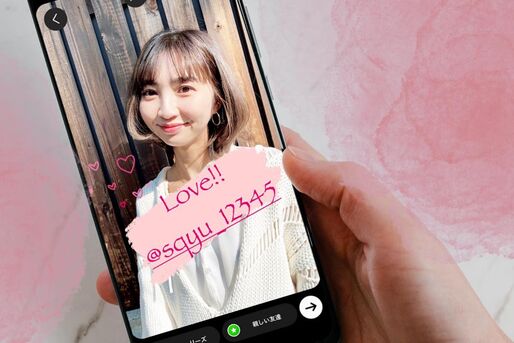
インスタストーリーの文字入力では、デフォルトで用意された9種類のフォントの他に、裏技を使わないと出現しない隠れフォント「pupyrus(パピルス)」があるのをご存知でしょうか。本記事では、インスタストーリーで隠れフォントを出す方法を解説します。
ストーリーの隠れフォント「papyrus(パピルス)」を出す方法
ストーリーを見ていると、カリグラフィーのようなアンティーク風書体で文字入力がしてある投稿が流れてきたことはないでしょうか。
上の画像で使われている文字は「パピルス(papyrus)」というフォントを使用したもので、手書きのような曲線と、文字の外側がチョークで書いたようにかすれているのが特徴。海外風の加工が好き、あるいはレトロっぽい雰囲気が好きといったユーザーにおすすめの書体です。
このパピルス文字は、ストーリーで使えるデフォルトのフォントではないため、裏技を使って出現させる必要があります。本記事で紹介する隠れフォントはiOS版Instagramでのみ利用ができ、Android版では使えません。
ストーリーの投稿画面で「Aa」(文字入力)の部分をタップする
まずは、ストーリー作成画面で写真や動画を選択後、[Aa]ボタンをタップし、文字入力の状態にします。
「papyrus」と入力する
続いて、英字で「papyrus」と入力してください。キーボードの予測変換を使って「パピルス」と入力してもOK、正しい英字が反映できます。
綴りを間違えてしまうと隠れフォントが出てこないので、注意してください。
右から4つ目のフォントに設定
「papyrus」の状態で、フォントを右から4つ目まで移動させてください。隠れフォントに切り替わるはずです。
うまく切り替わらない場合は、「papyrus」と入力したまま右端のフォントに戻し、1個ずつ左にずらしてみてください。
「papyrus」を消して、入力したいワードを打ち直す
「papyrus」の文字を消します。文字を一文字ずつ消去しても、一気にすべて消去してもOKです。
続いて入力したいワードを打ち直すと、パピルス文字の状態で文字入力ができるはずです。
「@メンション」や「#ハッシュタグ」もパピルス文字にできる
ストーリーでパピルス文字が使えない・反映されない原因
前述の手順通りに進めても「papyrus」の隠れフォントがうまく反映されない場合、以下の原因が考えられます。
Android版インスタグラムを使っている
隠れフォント「papyrus」は、iOS版インスタグラムでのみ使用できます。Android版を利用している場合は、パピルス文字が反映されません。
「papyrus」の綴りを間違えている
「papyrus」の綴りが間違っている可能性があります。「pupyrus」「papyris」などの綴りミスをすると、フォントが反映されないので、入力した英字が正しいかどうかを確認してみてください。
選択すべきフォントを間違えている
右から4つ目のフォントが正解
フォント選択が違うと反映されない
選択中のフォントは、右から4番目のものになっているでしょうか。
フォント選択を間違えると「papyrus」がうまく反映されないので、左右に1つずつフォントをずらしてフォントを切り替えましょう。
全角英字・全角数字・ひらがな・漢字には適用されない(半角数字はOK)
隠れフォント「papyrus」は、以下の文字には反映されません。
- ひらがな
- カタカナ
- 漢字
- 全角英字
- 全角数字
半角英数字であれば適用されます。また、「@メンション」や「#ハッシュタグ」を半角英数字でパピルス文字にしてもOKです。